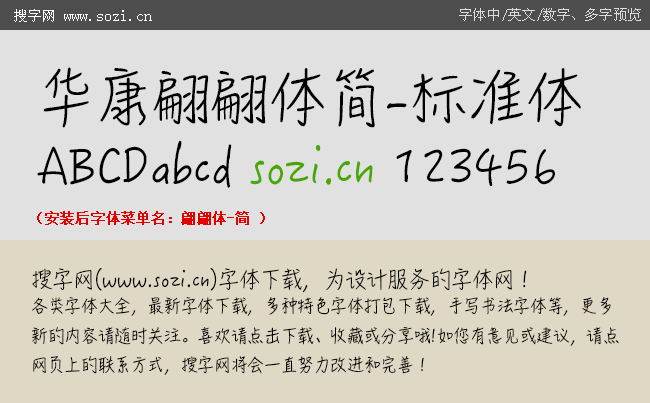
華康翩翩體簡-標(biāo)準(zhǔn)體
搜字網(wǎng)提供一款手寫風(fēng)格的華康翩翩體中文字體下載。華康翩翩體是一款硬筆風(fēng)格的書法字體,字呈長型,右上揚(yáng)起,清秀灑脫,筆觸帶著俏皮的律動感,整體活潑生動,呈現(xiàn)自然手感,是一套親和隨興的手寫字體。適用于海報(bào)設(shè)計(jì)、包裝設(shè)計(jì)、網(wǎng)頁設(shè)計(jì)等廣告設(shè)計(jì)場合。